现代设计的关键词中离不开“几何化”这一关键特点,从具象到抽象、从装饰到实用,这是设计理念的不断演变历程,这一历程中,几何化扮演了不可替代的作用,仔细观察今天我们身边的一切,不论是建筑还是家具、以及电子产品或交通工具,其造型的特点都可以归咎为一点:“几何化”,那么字体设计也不例外,从包豪斯时代,设计师就开始探索将字体设计的越来越几何化,去除多余的细节和装饰:
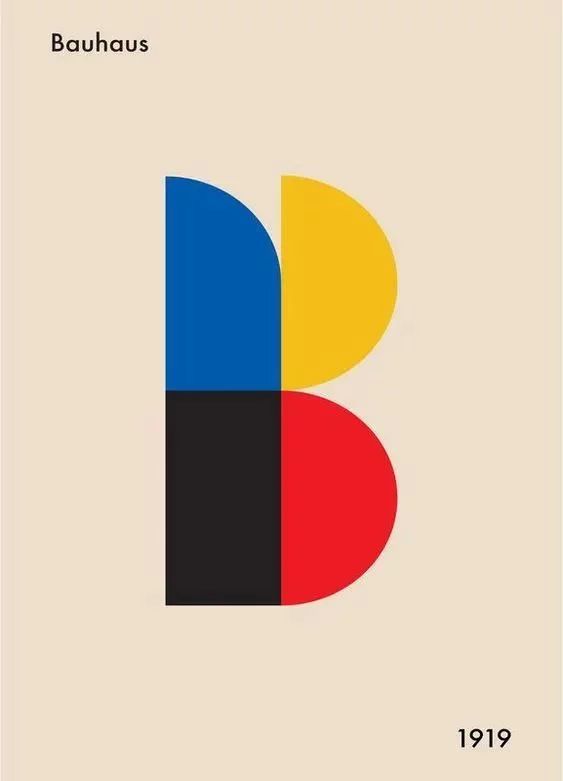
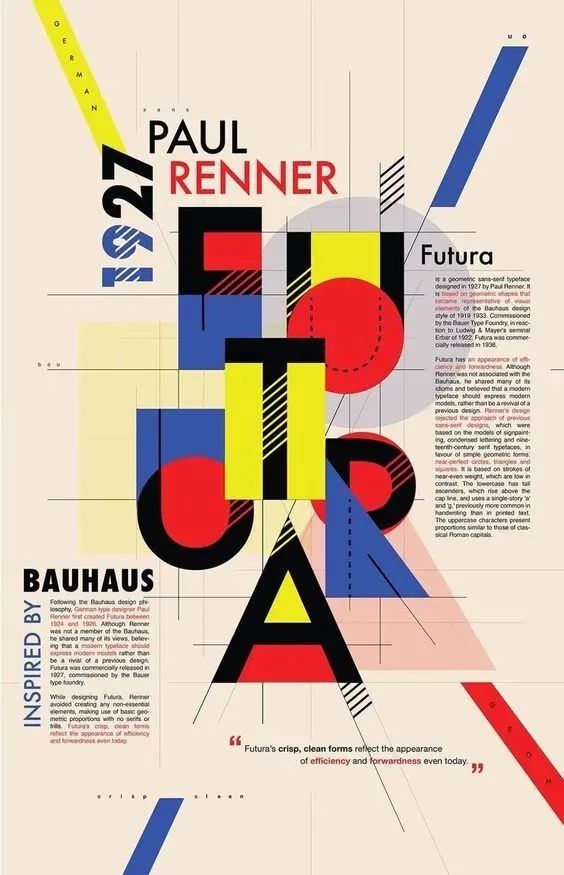
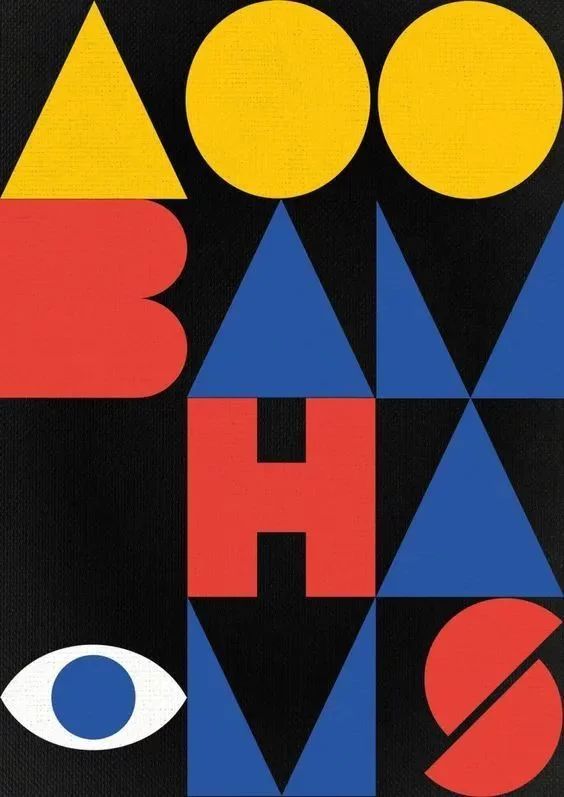
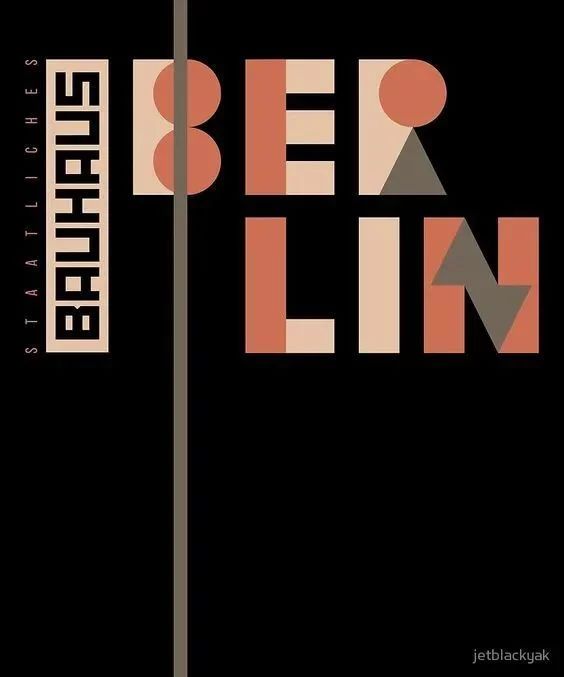
几何化的设计理念一直影响到今天,事实上,我们今天多看到的绝大多数设计作品,都离不开几何化的影子,字体设计也不例外,比如汉字中的黑体就是汉字几何化的代表,但早期的黑体依然保留了一定汉字的书写性特点,后续出现的黑体进一步削弱了书写性,使字体的几何化特点更加明显;不仅如此,就连许多设计大师也钟爱使用几何造字的方式去设计作品,我们来看一些例子:
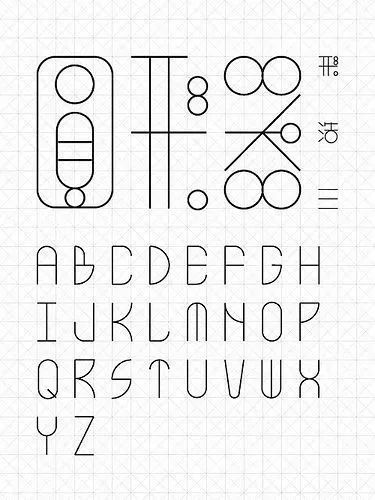
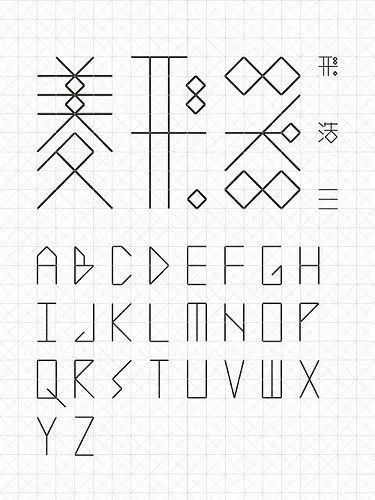
台湾设计师 Lai Chu-hsiu 作品
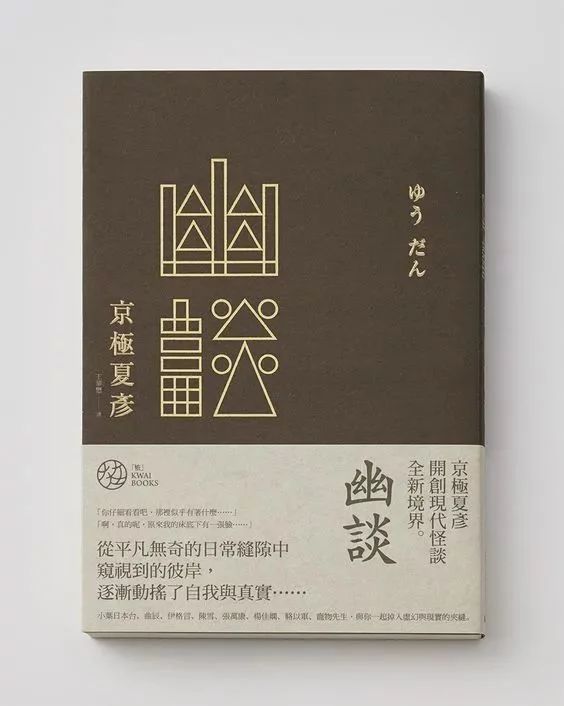
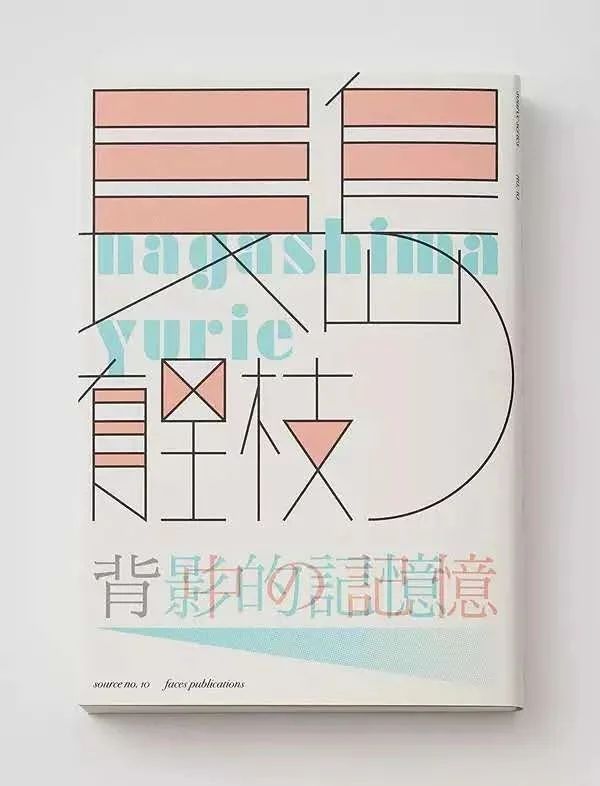
王志弘作品
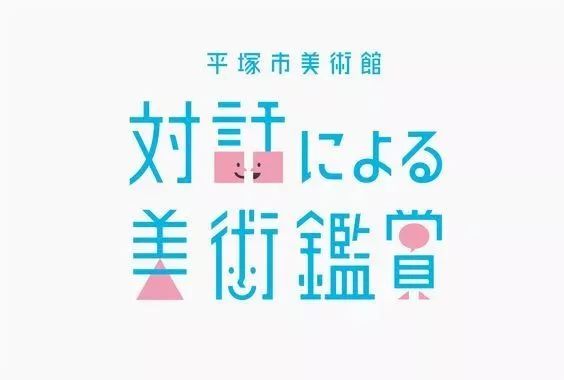
日本 tegusu 设计事务所作品
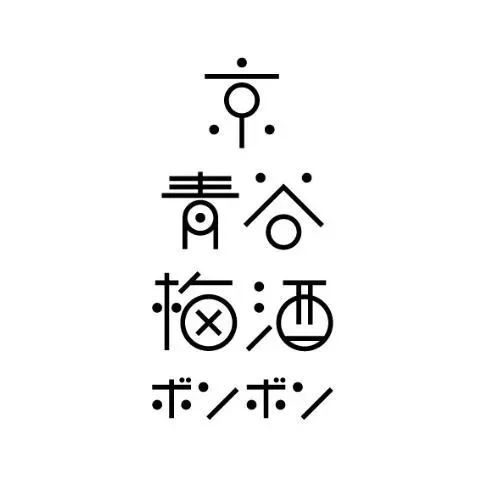
三木健作品
曾国展作品
看了这些大师的作品,你是不是也迫不及待的想学习一下如何设计几何字体呢?本篇我要讲的几个案例,是在不影响字体识别性的基础上,把字体最大限度的几何化,这种方法设计出来的字体,具有强烈的个性,也有很强的形式感和现代感,同时,通过对几何造字法的学习,让你学会如何去归纳和重组,用整体的眼光去观察,这是做字体设计必不可少的一种能力。
01
Sugar-coated shells
糖 衣 炮 弹
在做字之前我们使用矩形工具+直线工具,画出四个米字格作为辅助参考,这次我们同时在米字格内打出糖衣炮弹这四个字作为结构的参照。
做完这一步之后,我们就开始了观察和思考归纳的环节,需要注意的是,在用几何造字法做字时,整体的思维非常重要,在观察字体时,不要着眼于字体局部的某一个笔画,而是用整体的眼光去观察字形特征,找到适合的几何形去替代原有的字体笔画,当我们运用这种思维方式去观察字体时,就会发现糖字的米字旁, 可以归纳为上下两个三角形加中间一个长方矩形,如图:
沿着同样的思路,我们可以把“糖”字的右半边也用几何形归纳出来:
在归纳的时候,我们要用做减法的思路,尽量用最少的几何形去把字体表达出来,譬如唐字中间那部分笔画很复杂,我们经过归纳只用了两个矩形,这样不但加强了字体的形式感,同时也不影响字体的识别性,这就是是设计的巧妙之处,设计师唯有经过思考,才能有此创造;将笔画做几何归纳之后,再将其组合在一起,并做细微调整,加入一些细节,让字看上去更加的舒适:
这样,“糖”字的字形就设计完成了,接下来设计“衣”字,我们依然运用同样的思路,把衣字用几何形归纳出来:
这里我们依然沿用做减法的思路,在不影响字体识别性的基础上,最大限度地简化掉字体的一些细节,比如那一笔竖钩笔画的“钩”,就完全可以省去了,做这种形式的字体有点像搭积木的游戏,因为积木通常只有几种简单的几何形状,所以要用这些简单的几何形拼成一个文字,需要动一番脑筋。
接下来我们做“炮”字,炮字的左边是一个火字旁,经过观察,我们发现“火”字与“米”字在外形上有一定的相似之处,都可以用两个三角形来去归纳,右边的包字笔画几何特征比较明显,基本用矩形就可以归纳,归纳完之后如下图:
这时候我们发现,归纳完的几何形在识别性上有点差,并且左侧两个三角形的中间位置显得有点空,整体上来说与前两个字统一性不强,前两个字都有圆的元素,这个没有,基于这些问题,我们对其进行优化调整:
由于火字本身就带有“点”的笔画元素,因此我们把三角形做大小比例的调整,并把圆点加入进去,这一点的加入起到了“画龙点睛”的作用,这个字立马变得生动了起来,因为炮弹总能让人联想到圆形,所以在这个字的恰当位置加入一些圆形会让人在看到这个字体设计的时候产生相应的联想,“包”字里的口字结构也替换为圆形,就是为了达到这个目的。
最后是“弹”字了,这个比较简单,因为它的笔画结构90%都可以用矩形来呈现,唯一需要注意的是右边的“单”字,中间那部分笔画有点繁多,需要用减法,用一个矩形来概括处理,如下图:
单字上面的两点用圆形来替代,一方面与前面三个字相呼应,同时也更形象地传达出了“炮弹”的形象。
到此,这四个字的字形设计就完成了,接下来是最后一步,也是非常关键的一步:上色。
给字体添加颜色,是很关键的一步,如果颜色用的不好,很容易毁掉字体,糖衣炮弹这四个字从字形特点上来说属于比较有趣味性,属于比较好玩的字体,所以颜色上可以丰富一些,字面意思又包含了“糖”这种甜甜的含义,所以色彩可以贴近糖果的视觉感受,饱和度要稍微高一些的,能带给人食欲的色彩, 经过筛选和尝试,最终确定了以下这四种渐变色作为字体的色彩,均匀分布在四个字体当中:
加入了色彩之后,这四个字体立马变得生动了起来,贴近糖果的视觉感受,丰富又和谐的色彩,让整个作品的趣味性增强了不少。
02
MOYANSANJIE
魔 岩 三 杰
魔岩三杰这个案例的思路与糖衣炮弹基本一致,以整体的眼光对原有笔画进行归纳和概况,使用基本的几何形将字体归纳出来:
将颜色填充后,四个字的基本字型就基本完成了:
接下来,需要对字体进行进一步的微调,让四个字的视觉大小更加平衡,同时,目前四个字显得太平没有层次感,因此我们需要在PS中,给每一个几何结构加入渐变效果,渐变样式为 “角度” :
最后,对字体做上下结构的排版,加入英文和五角星图案,再添加一些杂色效果,这个案例就最终完成了,效果如下:
03
CH U R C H
教 堂
教堂这个案例,灵感来源于,教堂里拱形的彩色玻璃窗,尝试将教堂的笔画结构直线化放入一个拱形结构中后,非常符合,于是这个案例就顺利成章的做出来了:
在颜色的设置上,同样是提取了教堂玻璃的色彩,让人一看就自然联想到教堂:
好了,关于几何造字法,就先讲到这里,需要注意的是,在使用几何形进行归纳的时候,一定要选择与字体形状相符合的几何形,最终的字体一定要兼顾识别性和美观性,切勿在变形的过程中丢失了这两项最主要的指标。